Irlandske skrifttyper bærer på en dyb og fascinerende historie, der strækker sig tusinder af år tilbage til de tidligste middelalderlige manuskripter. Disse skrifttyper er mere end blot bogstaver; de er et vindue til Irlands kulturarv og æstetik, ofte præget af de samme kunstneriske traditioner, der ses i keltiske knuder og illuminerede manuskripter som den berømte Book of Kells. At forstå irske skrifttyper handler om at værdsætte en unik typografisk stil, der har overlevet tidens tand og stadig finder anvendelse i dag.
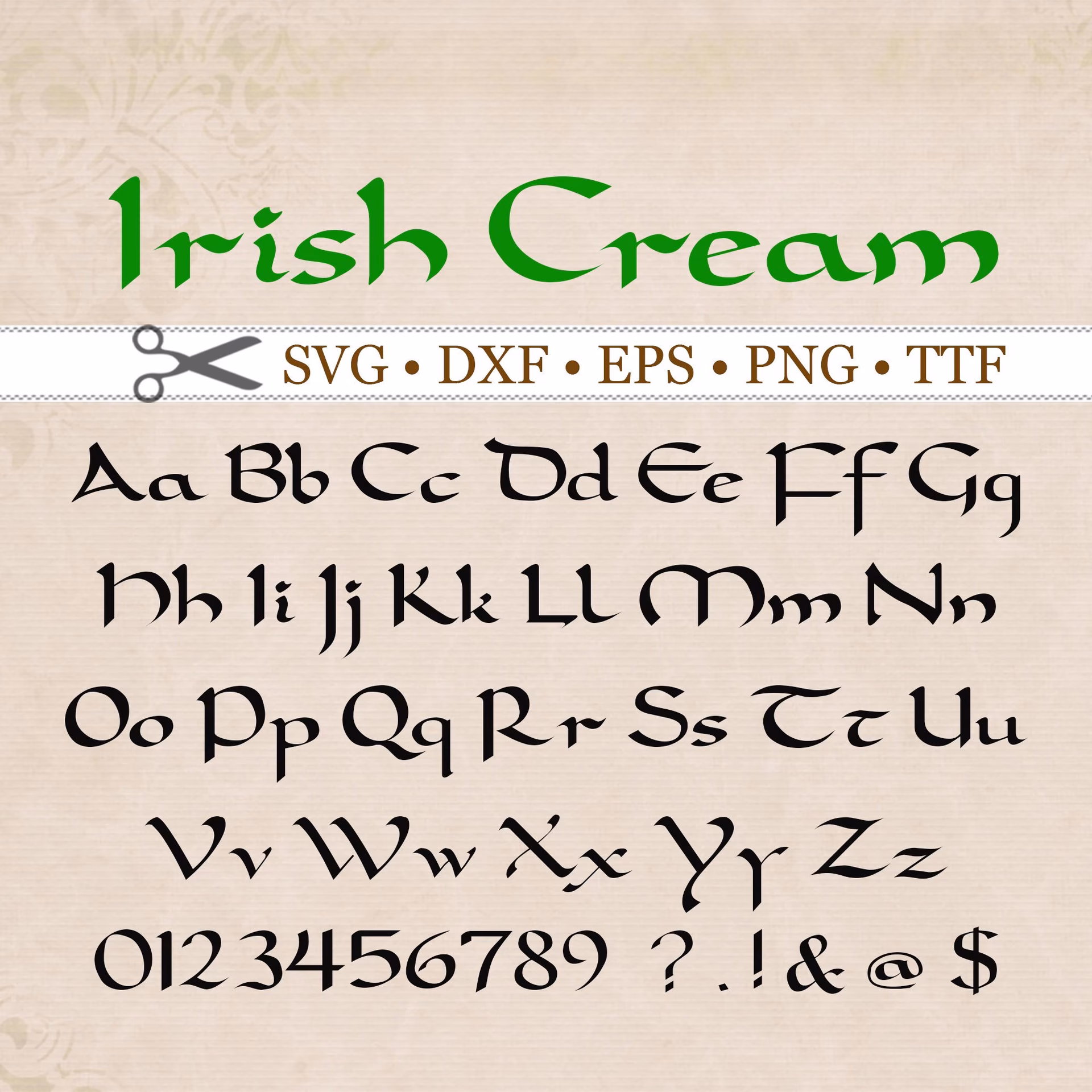
Hvad er det så, der præcist definerer en irsk eller keltisk skrifttype? Typisk deler de en række karakteristika, der adskiller dem fra mere almindelige latinske skrifttyper. Disse træk afspejler deres oprindelse i håndskrevne traditioner og en særlig visuel følsomhed. En af de mest fremtrædende egenskaber er de afrundede og flydende bogstavformer. I modsætning til de skarpere vinkler, man finder i mange andre skrifttyper, har irske skrifter ofte en blødere, mere organisk kurve, der minder om den måde, blækket flød fra en pen på pergament.
Ud over de grundlæggende 26 bogstaver i det latinske alfabet, inkluderer gaeliske skrifttyper også specifikke tegn, der er nødvendige for at skrive irsk korrekt. Dette omfatter alle vokaler med akut accent: Áá, Éé, Íí, Óó, Úú. Derudover er der en række konsonanter med en prik over: Ḃḃ, Ċċ, Ḋḋ, Ḟḟ, Ġġ, Ṁṁ, Ṗṗ, Ṡṡ, Ṫṫ. Disse prikker, kendt som séimhiú eller lenition, indikerer en ændring i konsonantens udtale. Et andet vigtigt tegn er det tironiske tegn et (⁊), som bruges i stedet for ordet 'agus', der betyder 'og' på irsk. Gaeliske skrifttyper indeholder ofte også insulære former for bogstaverne r og s (ꞃ, ꞅ) samt en række ligaturer, der stammer fra manuskripttraditionen. Det lille 'i' tegnes ofte uden en prik, og bogstaverne d, f, g, t kan have karakteristiske insulære former (ꝺ, ꝼ, ᵹ, ꞇ). Mange moderne gaeliske skrifttyper understøtter også bogstaverne j, k, q, v, w, x, y, z med gaeliske former og giver typisk understøttelse for vokalerne i andre keltiske sprog. De skelner også traditionelt mellem tegnet '&' og det tironiske tegn '⁊', selvom nogle moderne fonte erstatter ampersand med det tironiske tegn.
Oprindelsen af den irske unciale skrift kan spores tilbage til middelalderlige manuskripter, hvor den udviklede sig som en 'insulær' variant af det latinske alfabet. Disse skrifter opstod i Irland i det 7. århundrede og blev brugt helt op til det 19. århundrede, selvom deres mest blomstrende periode var mellem 600 og 850. De var tæt beslægtet med unciale og halvunciale skrifter, som var deres umiddelbare inspirationskilder. Den højeste kvalitet af insulær skrift er den majuskule insulære halvunciale, som er tæt afledt af kontinental halvuncial skrift. Den første gaeliske skrifttype til tryk blev designet i 1571 til en katekismus bestilt af Elizabeth I. Dette markerer et vigtigt skridt i overgangen fra håndskrevne manuskripter til trykt typografi i Irland.
Brugen af gaelisk skrift i tryk forblev almindelig i Irland indtil midten af det 20. århundrede. I dag bruges gaelisk skrift primært til dekorativ typografi. Selvom den ikke længere er standarden for brødtekst, har den en stærk plads i design, der ønsker at formidle en følelse af tradition, historie og irsk identitet. For eksempel trykker en række traditionelle irske aviser stadig deres navn i gaelisk skrift på forsiden. Det er også meget populært til pubskilte, lykønskningskort og reklamer, hvor det tilføjer et autentisk og iøjnefaldende element. Flere irske virksomheder og organisationer har brugt gaelisk skrift i deres logoer. RTÉ, Irlands nationale public service-kringkaster, skabte i 1996 et nyt virksomhedslogo, der var en moderne fortolkning af den gaeliske skrifttype. TG4, den irsksprogede tv-kanal, brugte også en modernisering af fonten i sit oprindelige logo under navnet TnaG. Andre eksempler inkluderer GAA (Gaelic Athletic Association), tidligere Telecom Éireann og An Post (det irske postvæsen). Det irske politi, Garda Síochána, bruger gaelisk skrift på sit officielle segl. Dette viser, at selvom skriften har ændret sig i sin primære funktion, forbliver den et vigtigt symbol på irskhed.
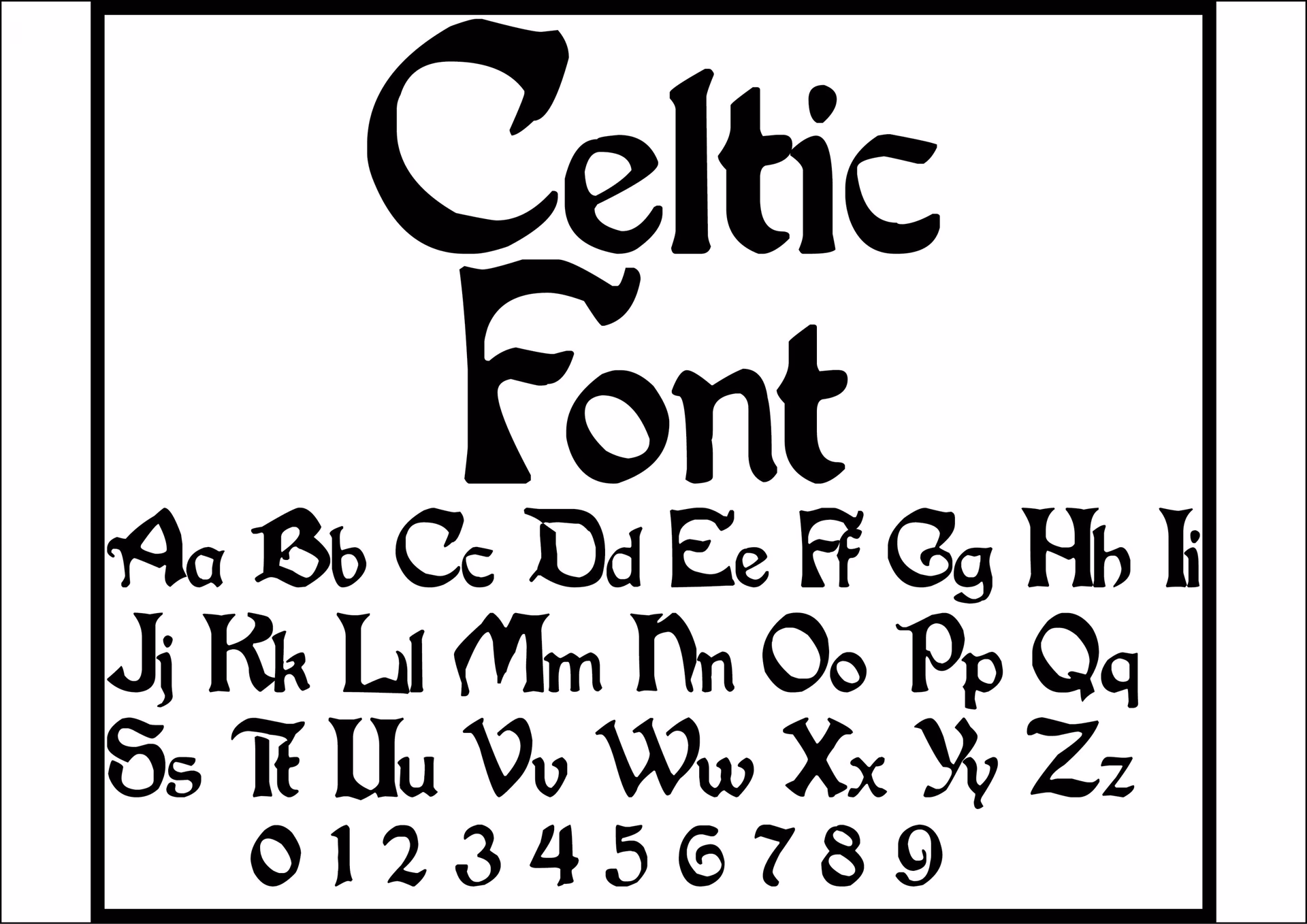
Der findes forskellige stilarter inden for irske og keltiske skrifttyper, som kan bringe et unikt og historisk præg til design. Uncial og gaeliske stilarter er særligt populære, ofte med de karakteristiske afrundede former og detaljer. Nogle fonte blander gotiske og unciale stilarter, hvilket gør dem ideelle til historiske og fantasy-projekter. Andre fokuserer på rene og alsidige unciale former, der fungerer godt til branding. Nogle er kendetegnet ved dristige strøg og skarpe kanter, der tilføjer et dramatisk præg, mens andre er mere elegante med raffinerede strøg inspireret af gamle keltiske bogstaver. Der er også fonte, der kombinerer klassisk keltisk charme med moderne læsbarhed, eller som er inspireret af naturen og keltiske traditioner for at tilføje et organisk touch.
Når man vælger den rigtige irske font til et design, er det vigtigt at overveje projektets formål. Til branding, hvor læsbarhed er afgørende, kan en stærk og læselig uncial eller moderniseret gaelisk font være et godt valg. Til mere dekorative eller tema-baserede designs, som f.eks. invitationer eller bogomslag, kan man omfavne fonte med detaljerede udsmykninger og middelalderlige elementer for at skabe en stemning. Nogle eksempler på digitale fonde baseret på traditionel gaelisk skrift inkluderer Duibhlinn (fra 1993, baseret på Monotype Series 24 A fra 1906) og Ceanannas (fra 1993, baseret på tegninger af Book of Kells bogstaver af Arthur Baker). Disse fonde søger at genskabe eller fortolke de historiske former for digital brug.
Et interessant eksempel på brugen af gaelisk skrift findes i pangrammer (sætninger, der indeholder alle bogstaver i et alfabet). Et sådant pangram på irsk, der viser mange af de specielle gaeliske bogstaver og former, lyder: Chuaigh bé mhórshách le dlúthspád fíorfhinn trí hata mo dhea-phorcáin bhig. Oversat betyder det noget i retning af: 'En meget sulten pige med en intens hvid, tæt spade gik gennem min gode lille grises hat'. En version af denne sætning skrevet med traditionel gaelisk skrift, der inkluderer prikker over bogstaverne og insulære former, ser således ud: Ċuaiġ bé ṁórṡáċ le dlúṫspád fíorḟinn trí hata mo ḋea-ṗorcáin ḃig. En anden sætning, der ofte bruges til at demonstrere fonten, er: Duibhlinn/Ceanannas an cló a úsáidtear anseo, hvilket betyder 'Duibhlinn/Ceanannas er fonten, der bruges her'. Disse eksempler illustrerer de unikke tegn og former, der er karakteristiske for gaeliske skrifttyper.
Når man bruger irske skrifttyper i design, er det ofte nødvendigt at parre dem med andre skrifttyper for at sikre god læsbarhed, især i længere tekster. En god strategi er at parre en dekorativ irsk font til overskrifter eller små mængder tekst med en enkel sans-serif eller serif font til brødtekst. Dette skaber en balance, der bevarer den keltiske æstetik uden at gå på kompromis med læsbarheden. Valget af parringsfont afhænger af den specifikke irske font og det ønskede udtryk, men målet er typisk at finde en font, der komplementerer, snarere end konkurrerer med, den irske skrift.
Irlandske skrifttyper, inspireret af den historiske insulære skrift, er tæt beslægtet med unciale og halvunciale skrifter. De udviklede sig med karakteristiske træk som afrundede former, specielle tegn for irsk og insulære bogstavvarianter. Disse træk er tydelige i manuskripter fra det 7. århundrede og frem. Den insulære halvunciale skrift, især, er en direkte efterkommer af kontinental halvuncial. Disse skrifter blev standarden i irske og anglo-irske manuskripter i århundreder og fortsatte med at påvirke trykt typografi, selv efter at mere standardiserede latinske skrifter blev almindelige. Deres vedholdenhed i dekorativ brug vidner om deres stærke kulturelle betydning.
Afslutningsvis tilføjer irske og keltiske skrifttyper et unikt og mindeværdigt præg til design, hvad enten det er til branding, bryllupsinvitationer eller tema-arrangementer. De er en fejring af Irlands rige historie og kunstneriske traditioner. Når man vælger en irsk font, er det altid en god idé at overveje licensbetingelserne, især hvis fonten skal bruges kommercielt.
### Ofte Stillede Spørgsmål
Hvad kaldes den traditionelle irske skrifttype?
Den traditionelle irske skrifttype kaldes ofte gaelisk skrift eller gaelisk skrifttype. Den stammer fra den insulære skrift, som udviklede sig fra unciale og halvunciale skrifter i middelalderlige irske manuskripter.
Hvad er de vigtigste karakteristika ved irske skrifttyper?
Vigtige karakteristika inkluderer afrundede og flydende bogstavformer, inklusion af vokaler med akut accent og konsonanter med prik over, brug af det tironiske tegn ⁊ for 'og', samt ofte insulære former for visse bogstaver (som r, s, d, f, g, t) og ligaturer.
Hvor stammer irske skrifttyper fra?
Irske skrifttyper stammer fra den insulære skrift, en variant af det latinske alfabet, der udviklede sig i irske middelalderlige manuskripter fra det 7. århundrede. Den første trykte gaeliske skrifttype blev designet i 1571.
Bruges irske skrifttyper stadig i dag?
Ja, irske skrifttyper bruges stadig i dag, primært til dekorative formål. De ses på avisforsider, pubskilte, lykønskningskort, i branding og logoer for virksomheder og organisationer, der ønsker at udtrykke en forbindelse til irsk kultur og historie.
Kan irske skrifttyper bruges sammen med andre fonte?
Ja, for at opnå god læsbarhed, især i længere tekster, er det almindeligt og anbefalet at parre irske skrifttyper (ofte brugt til overskrifter eller små mængder tekst) med enklere sans-serif eller serif fonte til brødteksten.